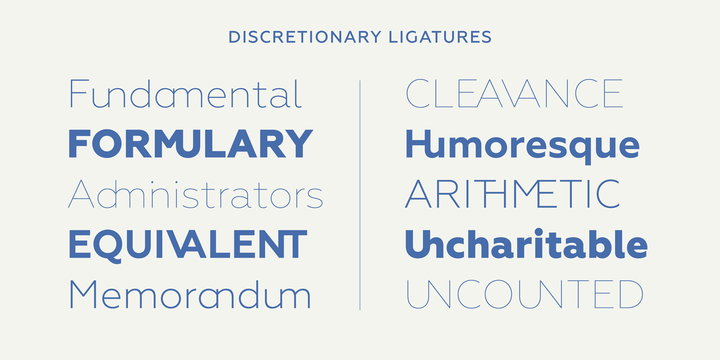
Interessante Schrift. Wie findest Du das Kernig (soweit man das am Bildschirm beurteilen kann)? Da habe ich bei Parachute machmal so mein Problem.
Das g finde ich einen Tick zu humanistisch für so eine geometrische Sans.
… gewagte Ligaturen
Wenn das mal kein neuer Trend ist. Die Glyphentabelle der Geometria ist auch voll davon.
Hm, was soll man den mit solchen Ligaturen anfangen? Na ja, vielleicht als Spielerei im Magazinbereich einsetzbar. Bei der Logogestaltung würde ich niemals auf solche vorgefertigten Spielereien zurückgreifen. Das könnte böse ins Auge gehen. Schlimmer als zwei Damen im gleichen Kleid bei der gleichen Veranstaltung …  ;-)
Davon abgesehen macht die Bague Sans aber einen netten Eindruck.
Sind für mich auch nicht wirklich Ligaturen. Jetzt nur auf teufelkommraus alles verschmelzen was die Buchstabenformen an Verschmelzungsmöglichkeiten hergeben, widerspricht ja teilweise auch dem Wesen einer Ligatur.
Der Meinung bin ich auch. Die Ligaruren funktionieren für mich überhaupt nicht!  :neenee:  Wenn man beim Lesen stockt und oder falsche Buchstaben liest, macht man die Schrift damit eher kaputt als dass man sie ausschmückt.
Ich denke, es kommt immer auf die Verwendung an.
Im vergangenen Jahr haben wir riesige Headlines in einer Ausstellung in der Avant Garde Gothic gesetzt, da hat es wunderbar gepasst.
Die Avant Garde ist aber auch noch mal ein ganz anderer Fall ... dort funktionieren die Pseudoligaturen geradezu parabelhaft. Mein erster Gedanke bei den Bague-Ligaturen war: Da hat jemand es Herb Lubalin gleichtun wollen, hat aber nicht funktioniert. Ist ungefähr so, als würde jetzt jemand auf Teufel komm raus was im 5/8-Takt spielen, nur weil's bei Brubeck so gut funktioniert hat. Manche Sachen scheinen wohl nur einmal zu klappen :-(